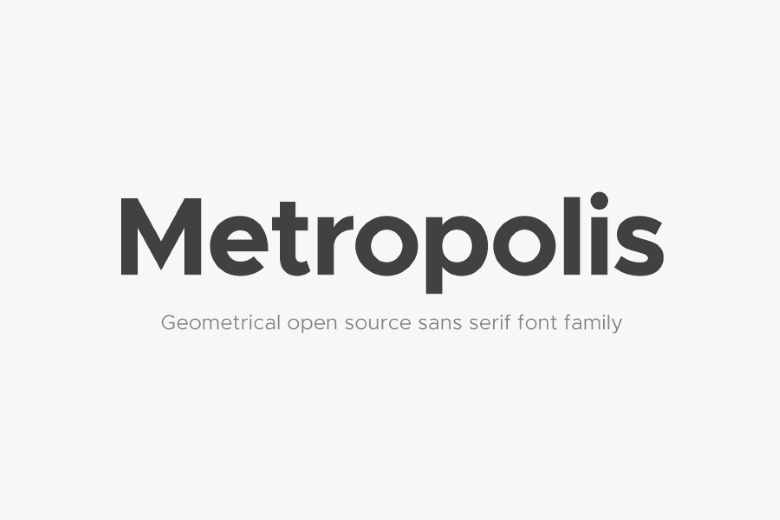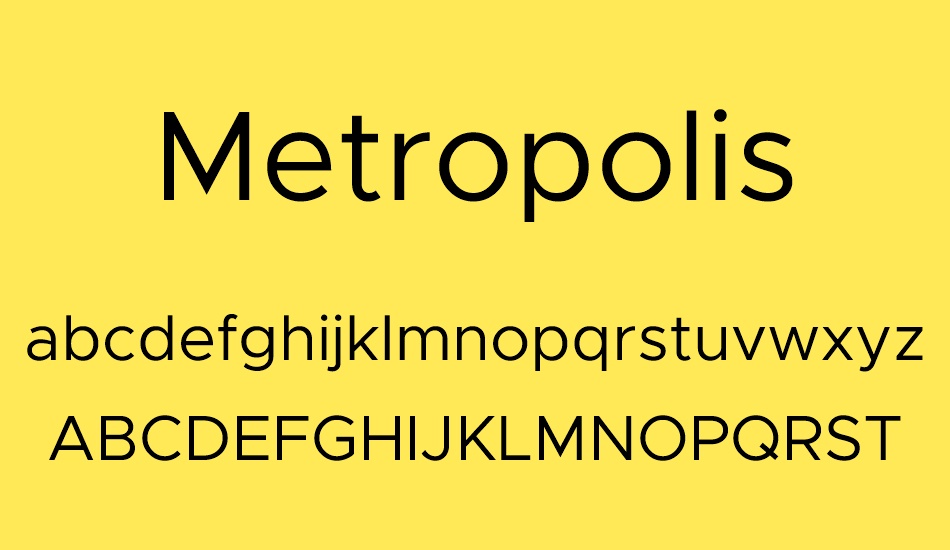
Metropolis font là gì và tại sao lại được ưa chuộng?
Metropolis font là một bộ phông chữ thuộc dòng Geometric Sans-serif (chữ không chân hình học) được thiết kế bởi Chris Simpson. Lấy cảm hứng từ những phông chữ kinh điển như Gotham hay Proxima Nova, Metropolis mang phong cách tối giản, hiện đại và vô cùng vững chãi. Đây là bộ phông chữ mã nguồn mở, cho phép các nhà thiết kế tự do sáng tạo mà không lo ngại về vấn đề bản quyền cho cả mục đích cá nhân lẫn thương mại.